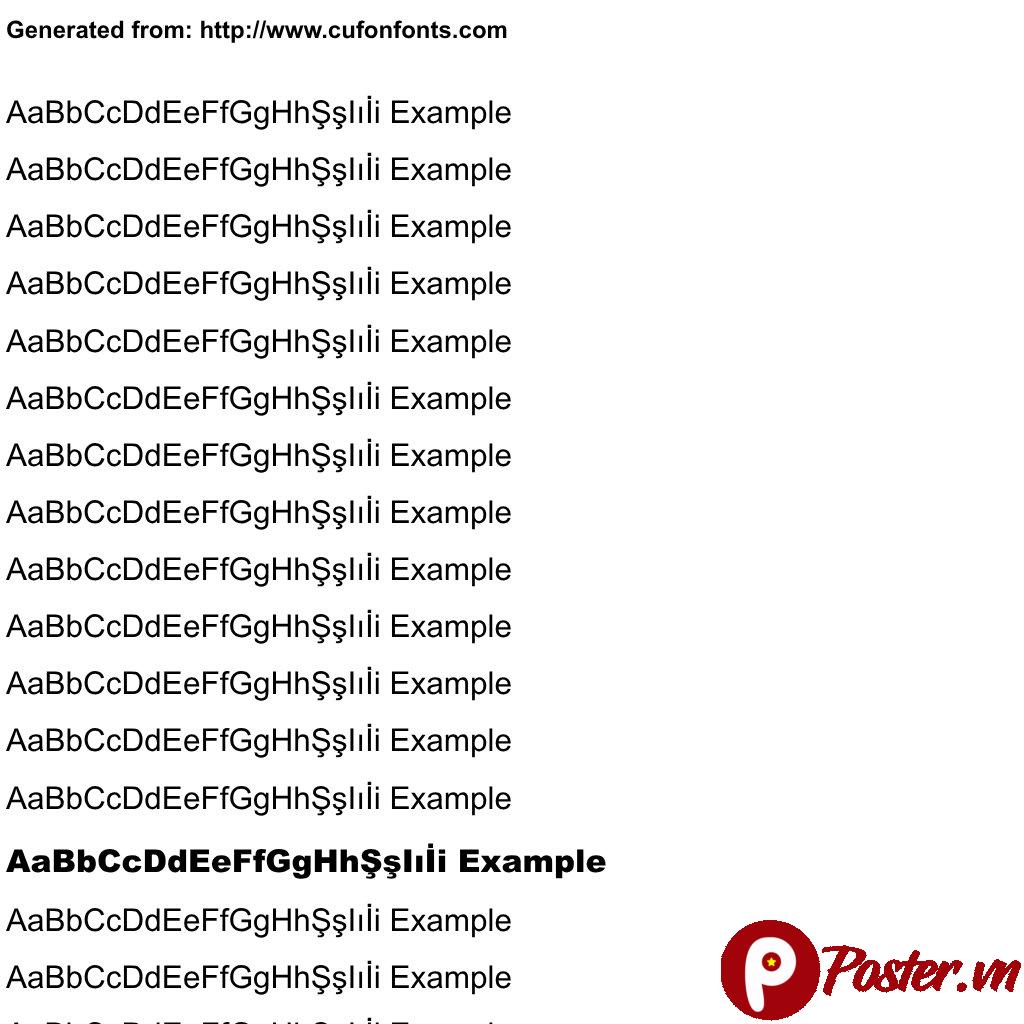
Font chữ Arial là một trong những kiểu chữ Sans-serif phổ biến nhất trên thế giới, được biết đến với tính dễ đọc, rõ ràng và khả năng ứng dụng rộng rãi. Tại Poster.vn, chúng tôi tự hào mang đến cho bạn bộ sưu tập font Arial đa dạng, bao gồm các biến thể quan trọng như Arial Regular, Arial Italic, Arial Bold, Arial Narrow và nhiều hơn nữa. Đây là những tài nguyên không thể thiếu cho mọi nhà thiết kế, từ người mới bắt đầu đến chuyên nghiệp, giúp tạo ra các ấn phẩm truyền thông chất lượng cao.
Tại sao Font Arial lại quan trọng trong thiết kế?
Font Arial được phát triển bởi Robin Nicholas và Patricia Saunders tại Monotype Corporation vào năm 1982. Mục đích ban đầu là tạo ra một kiểu chữ tương thích với Helvetica nhưng không phải trả phí bản quyền cho Linotype. Kể từ đó, Arial đã trở thành một phần không thể thiếu của hệ điều hành Microsoft Windows và nhiều ứng dụng khác, khiến nó trở thành một trong những font chữ được nhận diện rộng rãi nhất.
Tính dễ đọc và rõ ràng
Một trong những ưu điểm lớn nhất của Arial là tính dễ đọc. Các ký tự được thiết kế đơn giản, không có chân (Sans-serif), giúp mắt dễ dàng theo dõi, đặc biệt là trên màn hình kỹ thuật số và trong các văn bản dài. Điều này làm cho Arial trở thành lựa chọn lý tưởng cho các tài liệu văn phòng, báo cáo, trang web và ứng dụng di động.
Ứng dụng đa dạng
Với sự đa dạng về biến thể (Regular, Italic, Bold, Narrow, v.v.), Arial có thể được sử dụng trong hầu hết mọi ngữ cảnh thiết kế. Từ tiêu đề mạnh mẽ đến nội dung văn bản chi tiết, từ logo thương hiệu đến các ấn phẩm quảng cáo, Arial luôn thể hiện sự chuyên nghiệp và hiện đại. Sự linh hoạt này giúp các nhà thiết kế dễ dàng tạo ra sự nhất quán trong thương hiệu và truyền tải thông điệp một cách hiệu quả.
Các biến thể Font Arial nổi bật tại Poster.vn
Arial Regular
Đây là phiên bản cơ bản của font Arial, được sử dụng rộng rãi cho nội dung văn bản chính. Với độ dày vừa phải và nét chữ rõ ràng, Arial Regular đảm bảo tính dễ đọc tối ưu trong mọi kích thước và ngữ cảnh. Nó là nền tảng cho sự chuyên nghiệp và rõ ràng trong mọi tài liệu.
Arial Italic
Arial Italic mang đến một phong cách nghiêng nhẹ nhàng, thường được sử dụng để nhấn mạnh các từ, cụm từ hoặc trích dẫn. Sự thanh lịch của Arial Italic giúp tạo điểm nhấn mà không làm mất đi tính chuyên nghiệp tổng thể của thiết kế.
Arial Bold
Khi bạn cần làm nổi bật một tiêu đề, một đoạn văn quan trọng hoặc một lời kêu gọi hành động, Arial Bold là lựa chọn hoàn hảo. Với độ dày nét chữ tăng lên, Arial Bold thu hút sự chú ý ngay lập tức, giúp thông điệp của bạn trở nên mạnh mẽ và rõ ràng hơn.
Arial Narrow
Arial Narrow là biến thể có chiều rộng hẹp hơn so với Arial Regular, rất hữu ích khi bạn cần tiết kiệm không gian mà vẫn duy trì tính dễ đọc. Đây là lựa chọn tuyệt vời cho các thiết kế có không gian hạn chế như bảng biểu, biểu đồ, hoặc các ấn phẩm có nhiều thông tin cần hiển thị.
Các biến thể khác
Ngoài ra, Poster.vn còn cung cấp các biến thể khác như Arial Medium, Arial Black, Arial Rounded MT Bold, v.v., mỗi loại mang một đặc điểm riêng biệt, giúp bạn có thêm nhiều lựa chọn để sáng tạo và thể hiện phong cách độc đáo của mình. Sự đa dạng này đảm bảo rằng bạn luôn có công cụ phù hợp cho mọi dự án.